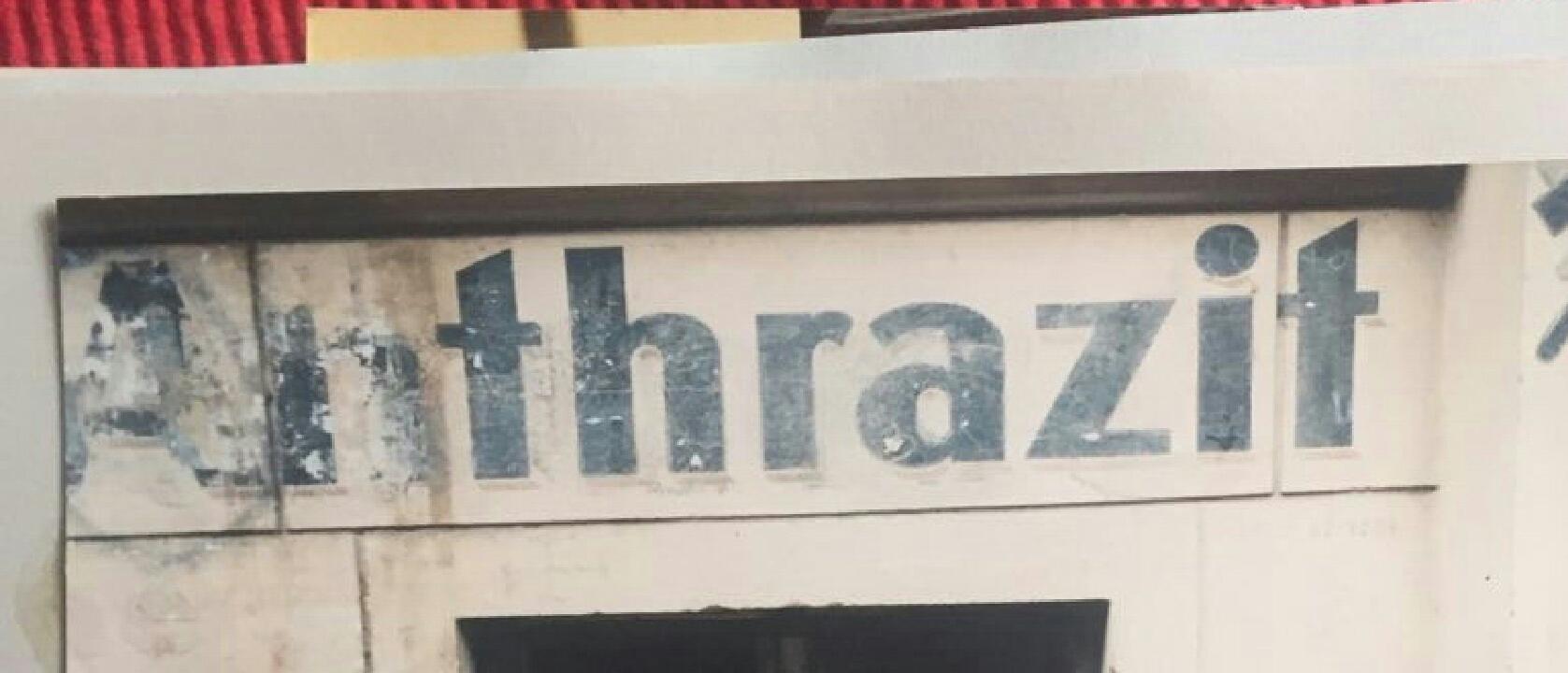
Fassadenschrift aus den 20er Jahren (Berlin)
Mein Schwiegervater möchte einen alten Schriftzug an einem Berliner Mietshaus restaurieren lassen, es sind aber nur noch wenige der Lettern erhalten. Hat diese Schrift einen Namen bzw. welche benannte Schrift ist dieser so ähnlich, dass man sie ersatzweise verwenden könnte?
geht es nur um das eine wort oder ist das nur eines von vielen? wenn es nämlich nur um »Anthrazit« geht, sollte es kein problem sein, das »n« aus dem deneben stehenden »h« abzuleiten. das »A« ist auch leicht.
wenn es allerdings mehr wird, wird es vermutlich schwierig. genau die gleiche schrift wird es wahrscheinlich nicht als font geben. aber da gibt es hier bessere auskenner als mich, die dir alternativen zur näherung geben können.
Da muss ich nachfragen. Ich melde mich nachher noch einmal.